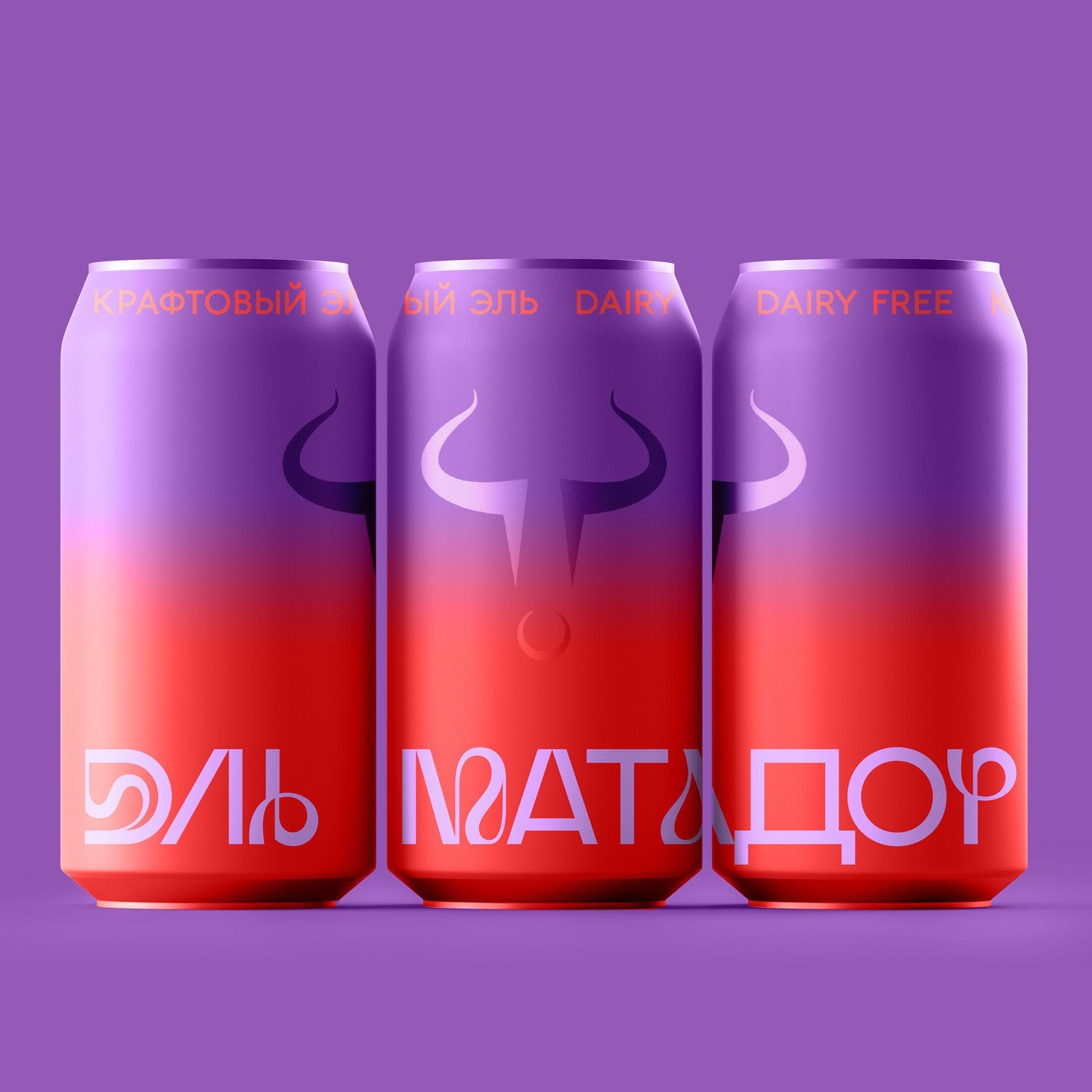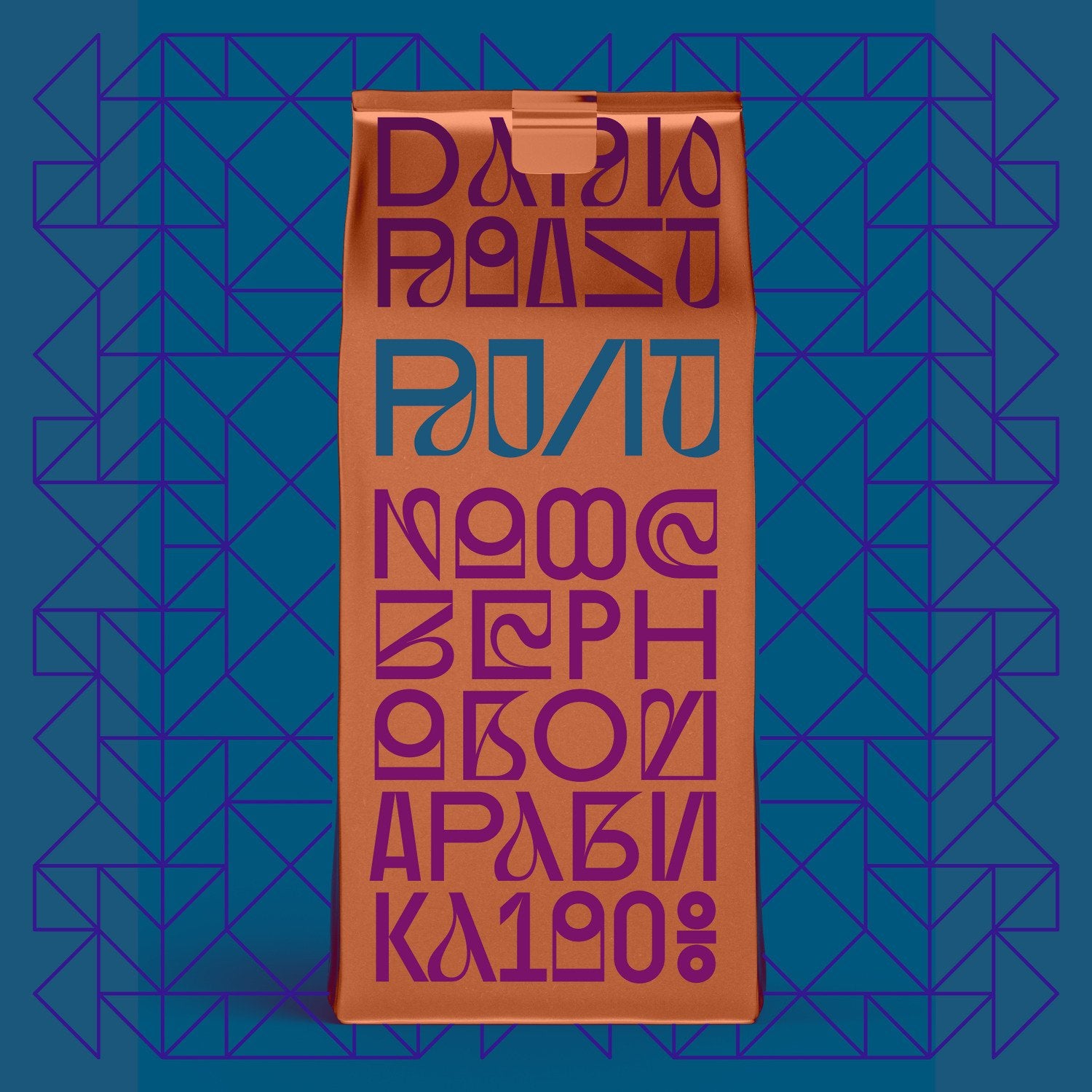
Tipografía BASE&BLOOM
BASE&BLOOM es una fusión experimental de una sans serif geométrica monolineal y una Didone de alto contraste con florituras. Inspirada en la escasez de fuentes sans serif modernas de exhibición innovadoras en comparación con el auge de las serif contemporáneas, reimagina las florituras como partes integrales de las formas de las letras en lugar de trazos decorativos. Este enfoque, especialmente único para una sans serif, da como resultado soluciones de formas de letras inventivas y dinámicas.
Con hasta 11 alternativas por letra, BASE&BLOOM ofrece combinaciones infinitas para crear el aspecto perfecto. Ideal para carteles, portadas de álbumes, branding, empaques, titulares, tipografía de gran tamaño y diseño editorial, es una opción audaz y versátil para creativos modernos.
Características
• 1257 Glifos
• 7 conjuntos estilísticos
• Conjuntos de caracteres: Latino europeo / Cirílico
• Alternativas
• Diacríticos
• Números
• Puntuación
• Símbolos